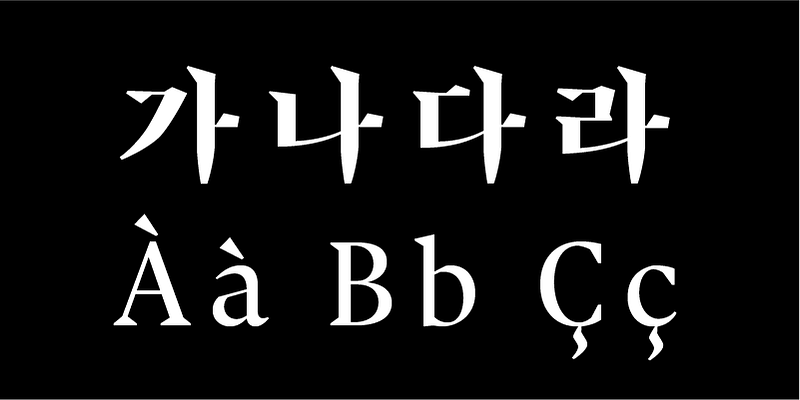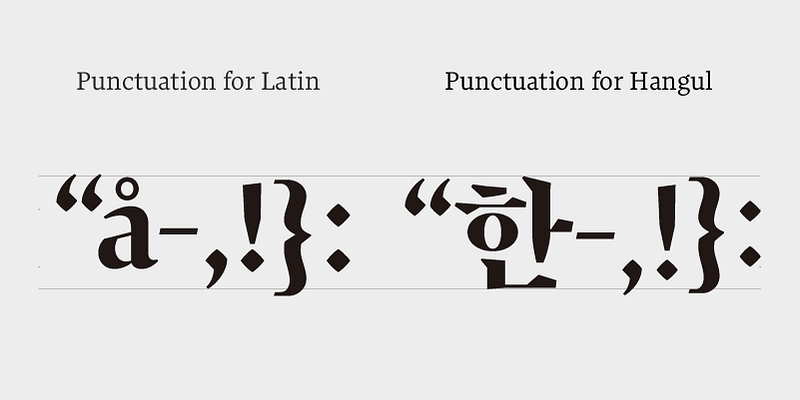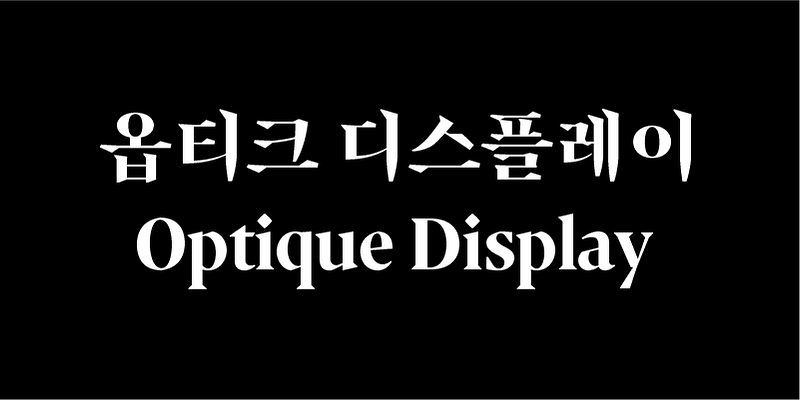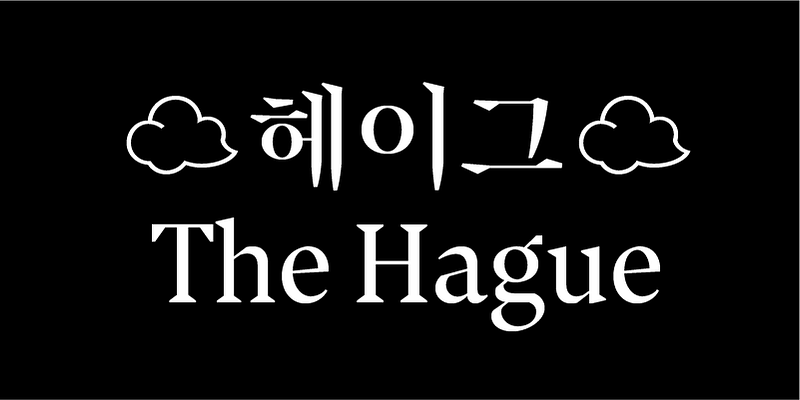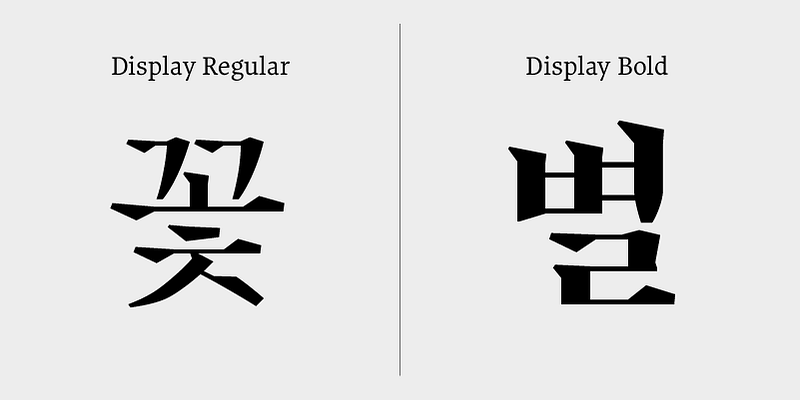
« Optique » est une police avec empattement basée sur les outils de chaque script ; plume large pour le latin et pinceau pointu pour le hangul. Optique simplifie les formes du latin et du hangul tout en préservant l’écriture de chaque script. Elle est conçue pour atteindre une certaine harmonisation ; afin que les deux scripts semblent ne faire qu’un. Elle se compose de trois styles : texte normal, affichage normal et gras. Les versions « Optique Display » sont destinées à se démarquer et à créer une ambiance qui attire le lecteur vers le texte. Elles présentent un contraste élevées, avec des empattements plus prononcés.